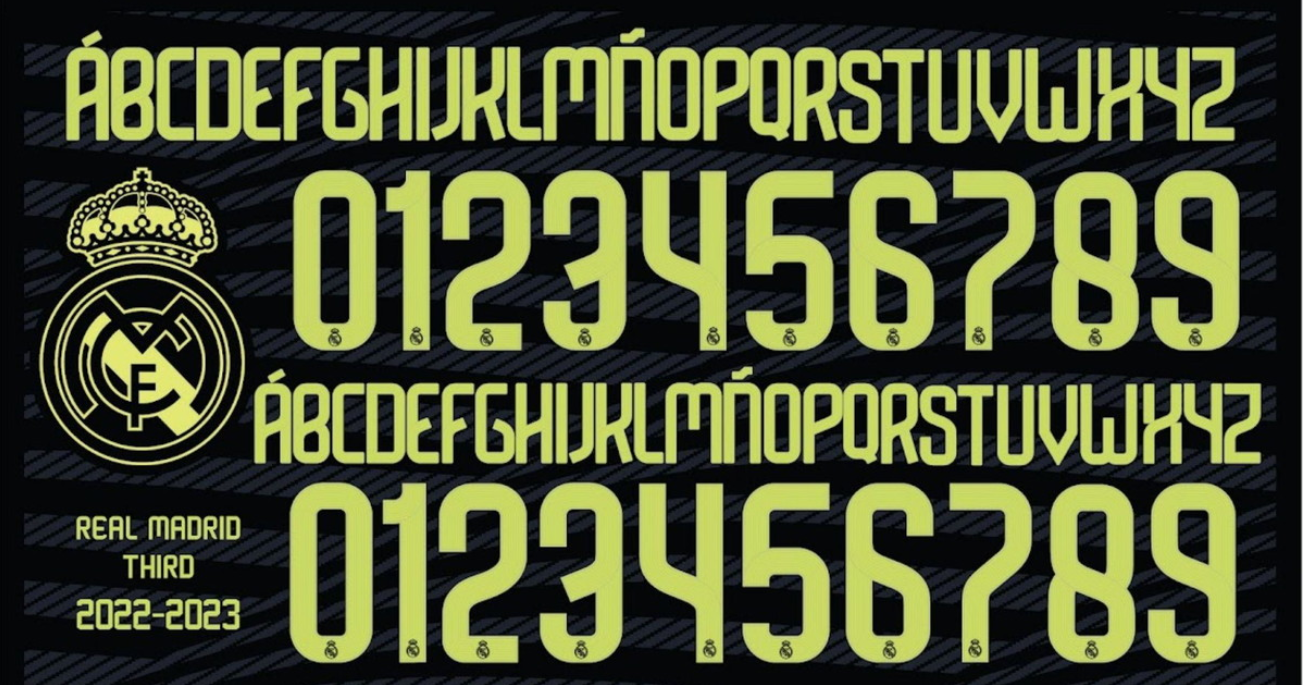
A elegância e a tradição se encontram no terceiro uniforme do Real Madrid para a temporada 23/24. Conhecida como a camisa da “Champions”, a peça preta com detalhes em amarelo dourado (carbono e ouro) exige uma tipografia à altura da grandeza do clube.
Neste post, trazemos a fonte exclusiva utilizada pelos Merengues em competições europeias e copas nacionais. Diferente da fonte genérica usada em La Liga, esta tipografia carrega o DNA da Adidas e o estilo único escolhido para estampar as costas de craques como Vinícius Jr. e Jude Bellingham.
- Conteúdo: Alfabeto completo e numeração oficial com o detalhe interno (inline) característico.
Estilo Visual da Fonte
A tipografia do Real Madrid para o Third Kit apresenta um design moderno com toques clássicos. Ela se destaca pela geometria limpa, sem serifas excessivas, o que garante excelente legibilidade mesmo à distância.
O grande diferencial visual desta versão é a harmonia com a cor preta da camisa. A fonte foi desenhada para ser aplicada no tom “Carbon” ou Dourado, transmitindo uma sensação de luxo e sobriedade. É a escolha perfeita para quem deseja reproduzir a camisa usada nas noites de glória da UEFA Champions League.
Dica de Especialista: Para um resultado 100% fiel à camisa de jogo da Adidas, utilize a cor amarelo-ouro (Gold) para os nomes e números na camisa preta.